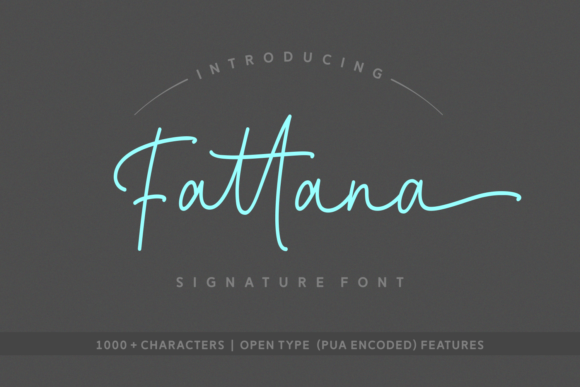
Fattana Script Font – Fonte Grátis
Fattana Script Font
Descubra uma nova adição à sua biblioteca de fontes, a Fattana Font do designer Hamilton. Perfeita para aqueles que valorizam um estilo elegante e sofisticado, esta assinatura única é ideal para headlines e design editorial. Fattana é uma fonte monoline e fina que oferece um aspecto moderno e clean, perfeito para dar vida a seu trabalho de design. Se você busca algo autêntico e único, essa fonte é uma escolha ótima. Experimente incorporar a Fattana Font em seus projetos e veja como ela pode transformá-los de maneira única e elegante.